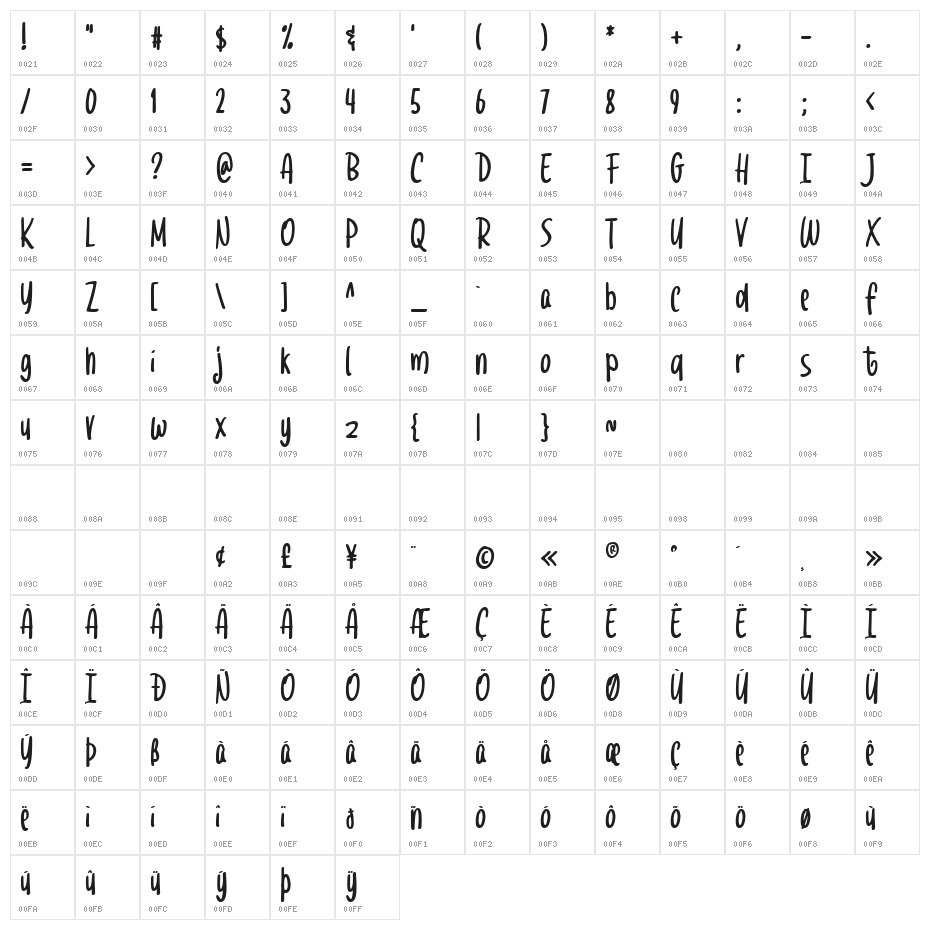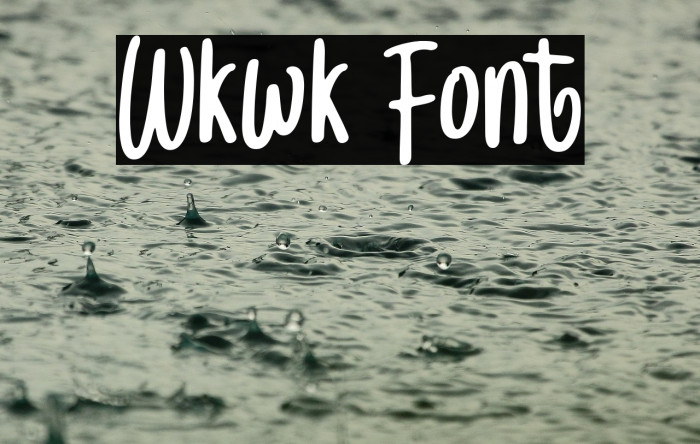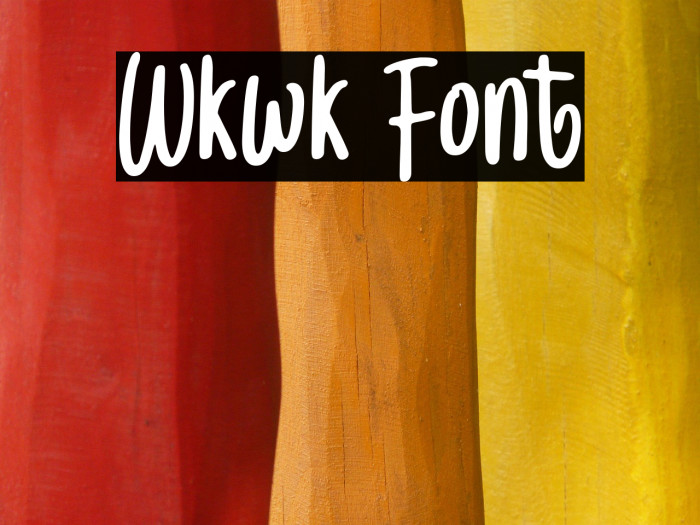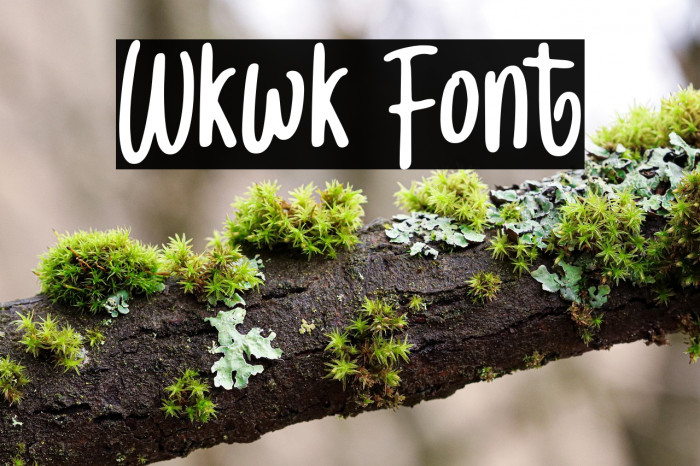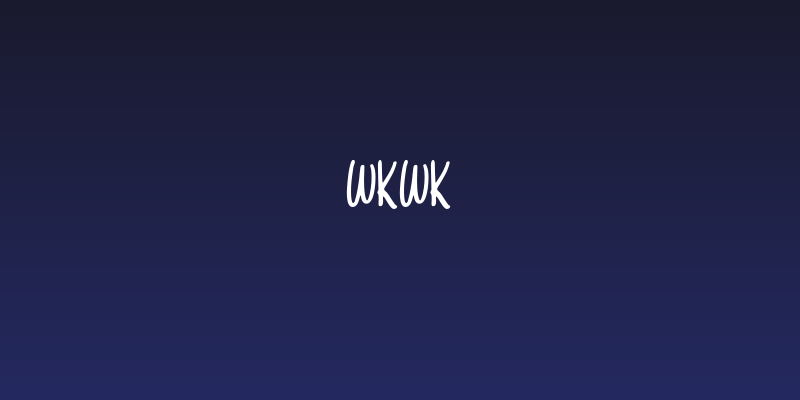
Wkwk Font
| Stile generale | Casual, Playful |
| Caso d'uso | Headlines, Logos, Creative projects |
| Progetti proposti | Ideal for children's books, playful branding, greeting cards, and creative social media graphics. |